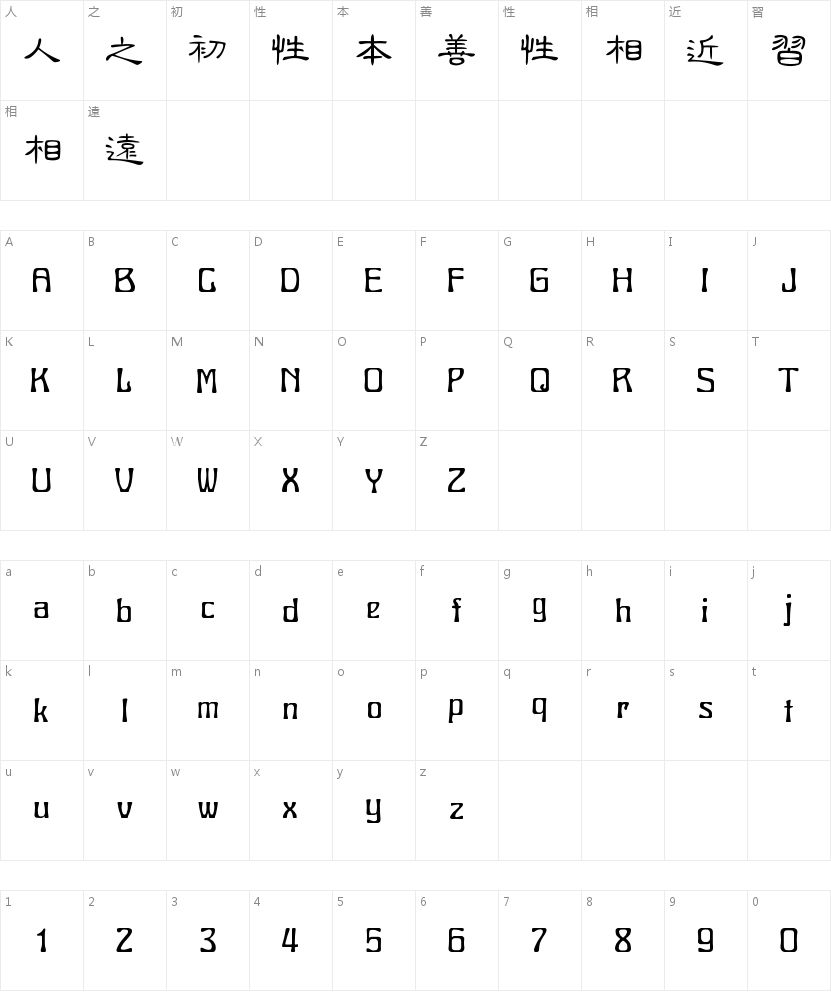
全真中隶书
全真中隶书是一种由宋代诗人苏轼创作的中国传统字体,也称为“苏轼字体”。它是以宋代古书文字为基础,以苏轼的书法特点和风格为特点,融合了楷书、行书、隶书和草书的特点,形成一种具有独特风格的书法字体。全真中隶书字体以笔画简洁、结构严谨、表达清晰、字型挺拔、构图美观、笔锋流畅等特点而著称。它具有清新自然、淡雅优美的特点,是中国书法史上一种重要的书法字体。
全真中隶书是一款非常不错的手写艺术字体,具有很好的视觉感,适合于文化类的宣传设计、商业类品牌的广告和产品包装设计以及个性化文字排版等较多场景。